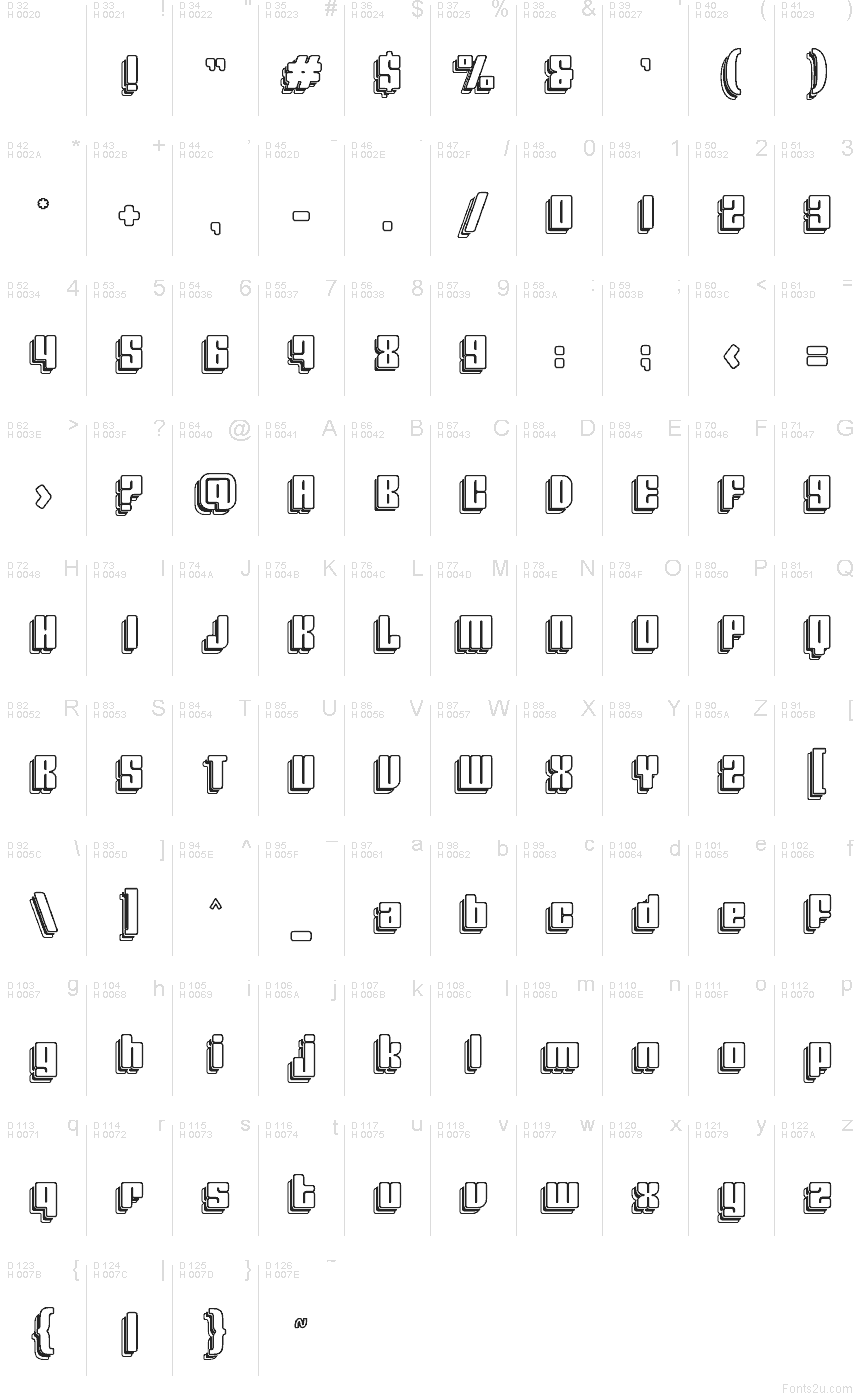
Dynamic Display Nine od Putracetol Studio je bezplatné retro 3D písmo typu display, které staví na podsaditých, zaoblených blokových tvarech a silných vrstvách odsazeného stínu. Tento opakovaný vrstvený obrys dodává písmenům siluetu připomínající nálepku s hravým nádechem arkádových nápisů, místo aby působilo jen plochým, geometrickým dojmem.
Široké tvary a výrazná hloubka z něj dělají přirozenou volbu pro názvy na plakátech, herní grafiku, obaly hraček, návrhy log a záhlaví na sociálních sítích. Nejvíce vynikne u krátkých slov, zejména pokud chcete, aby efekt vrženého stínu vytvořil styl sám o sobě bez nutnosti dalších dekorací nebo složitých pozadí.